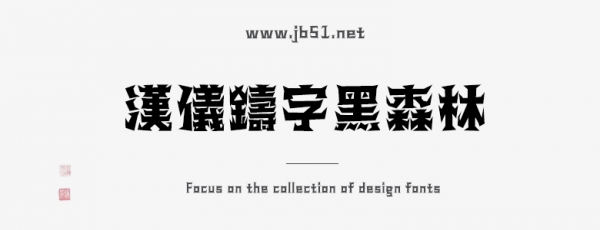
漢儀鑄字黑森林簡體/繁體一款不錯(cuò)的藝術(shù)字體,由漢儀字庫出品,字體筆畫處理突破常規(guī),靈活多變,厚重的字形中凸顯了幾分俏皮,具有很好的視覺感,適合應(yīng)用于藝術(shù)設(shè)計(jì)、平面宣傳設(shè)計(jì)、網(wǎng)頁設(shè)計(jì),書法字帖等領(lǐng)域,需要的朋友可以前來本站下載。